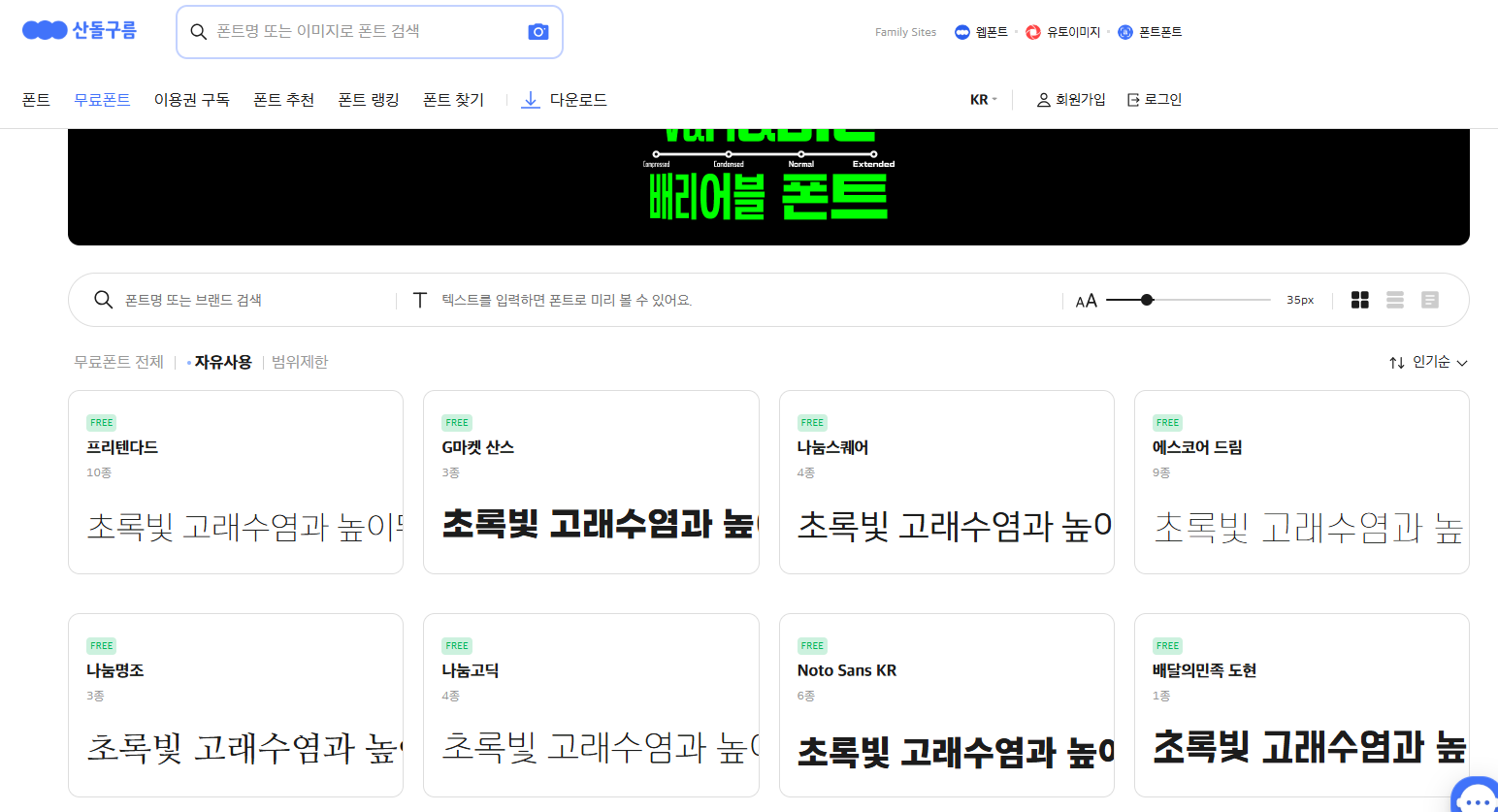
1. 네이버 나눔글꼴
네이버 나눔글꼴은 네이버에서 제공하는 무료 글꼴로, 상업적 용도로 사용할 수 있습니다. 나눔고딕, 나눔명조, 나눔스퀘어 등 다양한 서체를 제공합니다. 다양한 분야에서 사용하기 좋고, 특히 웹사이트나 프레젠테이션에서 많이 활용됩니다.
추천 글꼴:
• 나눔고딕: 깔끔하고 모던한 느낌의 글꼴로, 가독성이 뛰어나 다양한 문서와 웹사이트에 적합합니다.
• 나눔명조: 전통적인 세리프 글꼴로, 고급스러운 느낌을 주며, 책이나 신문에 적합합니다.
• 나눔스퀘어: 사각형 모양의 현대적인 글꼴로, 간결한 디자인을 원하는 웹사이트에 잘 어울립니다.
사용 예시:
• 나눔고딕: 기업 웹사이트나 블로그, 프레젠테이션에서 사용
• 나눔명조: 고급스러운 서적, 전단지, 포스터 디자인에 사용
2. 배달의민족 글꼴 (BMF)
배달의민족에서 제공하는 글꼴은 많은 디자이너들 사이에서 인기가 많습니다. 배민 주아체는 특히 친근하고 개성 있는 느낌을 주며, 배민체와 배민한마디체 등 다양한 스타일이 제공됩니다.
추천 글꼴:
• 배민 주아체: 귀엽고 친근한 느낌을 주며, 젊은 층을 대상으로 한 마케팅에 적합합니다.
• 배민한마디체: 세련되면서도 현대적인 느낌을 주어, 로고 디자인이나 광고 배너에 적합합니다.
사용 예시:
• 배민 주아체: 유머나 이벤트성 광고 디자인에 사용
• 배민한마디체: 브랜드 로고, 온라인 쇼핑몰 디자인에 사용
3. 카페24 고딕체 & 명조체
카페24는 무료로 사용할 수 있는 한글 글꼴을 제공하는 사이트로, 고딕체와 명조체를 제공합니다. 이 글꼴들은 상업적 프로젝트에서 자유롭게 사용할 수 있습니다.
추천 글꼴:
• 카페24 고딕체: 깔끔하고 직선적인 느낌을 주는 산세리프 글꼴로, 웹사이트, 블로그 등 다양한 곳에서 활용 가능합니다.
• 카페24 명조체: 세리프 글꼴로, 전통적이면서도 고급스러운 느낌을 줍니다. 문서나 책 디자인에 적합합니다.
사용 예시:
• 카페24 고딕체: 홈페이지, 블로그 포스트 디자인에 사용
• 카페24 명조체: 전단지, 리플릿, 브로셔 등에서 사용
4. 더페이스샵 잉크립퀴드체
더페이스샵 잉크립퀴드체는 손글씨 스타일의 독특한 폰트로, 현대적이고 개성 있는 디자인을 만들어 냅니다. 이 글꼴은 로고 디자인, 광고 배너, 초대장 등에 잘 어울립니다.
추천 글꼴:
• 잉크립퀴드체: 부드럽고 자연스러운 손글씨 느낌으로, 고급스럽고 세련된 느낌을 줍니다. 패션 브랜드나 뷰티 제품의 광고에 적합합니다.
사용 예시:
• 잉크립퀴드체: 화장품 브랜드 광고, 포스터, 배너 디자인에 사용
5. 티몬 몬소리체
티몬 몬소리체는 티몬에서 제공하는 한글 글꼴로, 유쾌하고 친근한 느낌을 주는 글꼴입니다. 이 글꼴은 광고, 팝업, 이벤트 디자인 등 다양한 상업적 디자인에 적합합니다.
추천 글꼴:
• 몬소리체: 단단하고 개성 있는 스타일의 글꼴로, 유머러스하거나 젊은 층을 대상으로 하는 디자인에 잘 어울립니다.
사용 예시:
• 몬소리체: 이벤트 디자인, 팝업 광고, 청소년 대상 광고에 사용
• 네이버 나눔글꼴: 깔끔하고 직관적인 글꼴 제공
• 배달의민족 글꼴: 개성 넘치는 친근한 디자인
• 카페24 글꼴: 다양한 웹 디자인에 적합한 글꼴
• 더페이스샵 잉크립퀴드체: 손글씨 느낌의 세련된 디자인
• 티몬 몬소리체: 유쾌하고 개성 넘치는 글꼴